2023년 최고의 둥근 글꼴 30개(무료 및 프리미엄)
게시 됨: 2023-07-23디자인 프로젝트에서 똑같은 오래된 글꼴을 사용하는 데 지치셨습니까? 작업에 신선하고 현대적인 느낌을 주고 싶습니까? 더 이상 보지 마세요! 이 블로그 게시물에서는 디자인을 한 단계 업그레이드할 수 있는 최고의 둥근 글꼴 30개를 공유합니다.
이제 둥근 글꼴이 정확히 무엇이며 왜 사용해야 하는지 궁금하실 것입니다. 둥근 글꼴은 가장자리와 곡선이 부드러워 친근하고 접근하기 쉬운 모양을 제공합니다.
디자인에 우아함과 독특함을 더하는 데 적합합니다. 또한 연구에 따르면 둥근 글꼴은 가독성과 몰입도를 높여 디자이너들 사이에서 인기 있는 선택이 되었습니다.
이 기사에서는 사용 가능한 최고의 둥근 글꼴 30개를 소개할 뿐만 아니라 각 글꼴에 대한 흥미로운 통계와 사실도 제공합니다.
로고를 디자인하든, 포스터를 만들든, 웹사이트에서 작업하든 이 글꼴을 사용하면 프로젝트에 더욱 세련되고 전문적인 마무리를 할 수 있습니다.
따라서 최고의 둥근 글꼴을 발견하고 이를 디자인에 통합하는 방법을 배울 준비가 되었다면 흥미진진한 타이포그래피 세계에 뛰어들어 탐험해 봅시다!
최고의 프리미엄 둥근 글꼴
Mountogen 반올림
Mountogen Rounded는 부드럽고 현대적인 둥근 글꼴로 디자인을 한 단계 업그레이드할 수 있습니다. 독특하고 강력한 특성으로 모든 프로젝트에 현대성과 개성을 부여합니다. 서체의 매력이 빛나므로 어떤 스타일과도 잘 어울립니다.
Mountogen Rounded의 눈에 띄는 기능 중 하나는 풍부한 대안과 합자입니다. 이러한 추가 기능은 디자인에 역동적이고 상호 작용적인 느낌을 주어 시각적 매력을 향상시킵니다.
책, 영화 포스터, 로고, 브랜딩 또는 명함 작업을 하든 Mountogen Rounded는 다재다능하여 디자인에 효과를 더할 수 있습니다.
Mountogen Rounded는 미적 측면에서 탁월할 뿐만 아니라 다국어 지원도 자랑합니다. 즉, 디자인하려는 언어에 관계없이 이 글꼴을 사용할 수 있습니다. 사용자 친화적인 특성으로 인해 모든 프로젝트에 쉽게 통합할 수 있어 시간과 노력을 절약할 수 있습니다.
라운드 블록
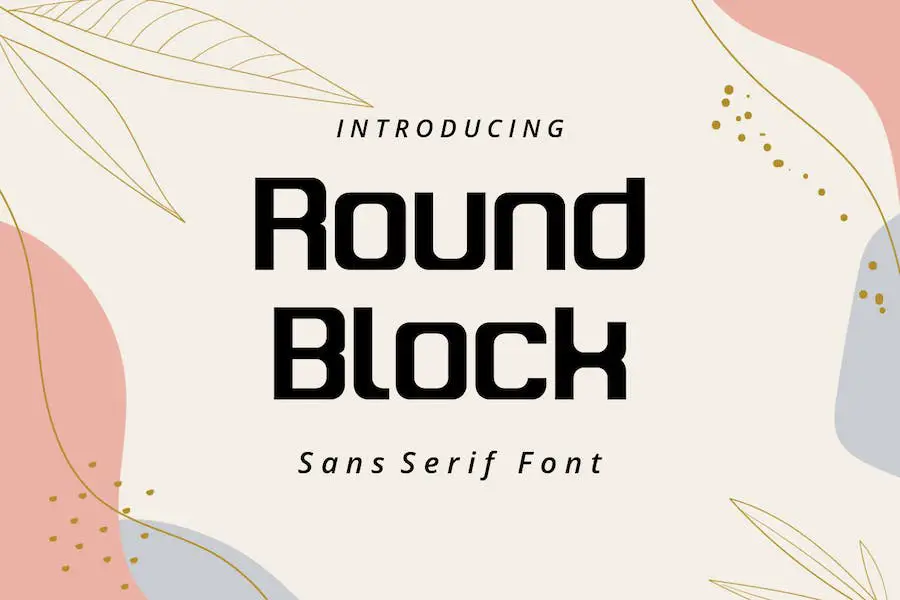
Round Block은 프로젝트를 향상시키려는 그래픽 디자이너에게 완벽한 현대적이고 부드러운 둥근 글꼴입니다. 테크노 산세리프 스타일로 스포츠 로고, 포스터, 헤드라인 및 인쇄 디자인에 현대적이고 세련된 터치를 더합니다.
이 다재다능한 글꼴은 표준 다국어 문자도 지원하므로 다양한 디자인 요구 사항에 액세스할 수 있습니다. 다가오는 이벤트를 위한 포스터 작업을 하거나 스포츠 팀의 로고를 만들 때 Round Block이 도와드립니다.
민트 라운드
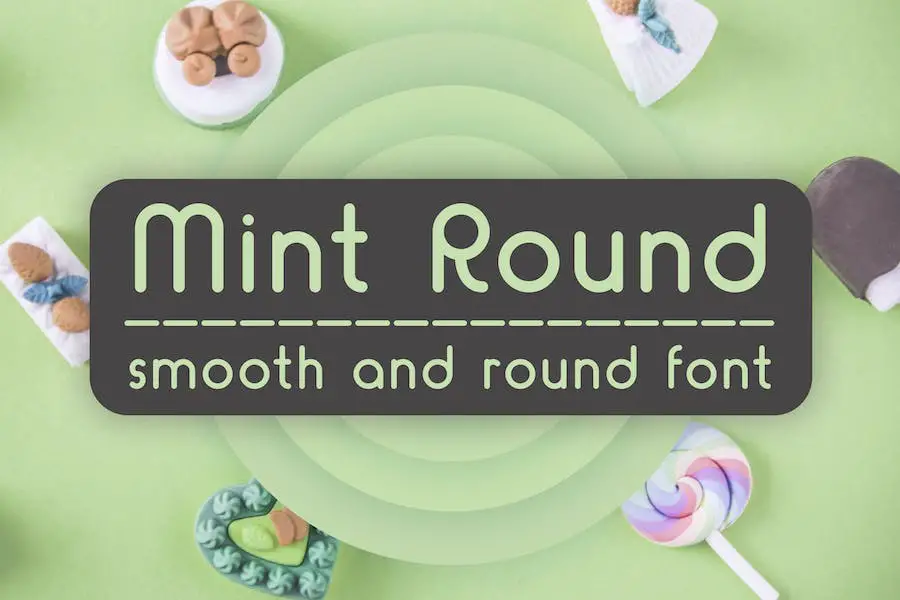
Mint Round는 디자인에 경쾌하고 현대적인 감각을 더해주는 부드러운 둥근 글꼴입니다. 단색, 윤곽선 및 인라인 변형이 있는 이 글꼴은 다양성과 창의성을 제공합니다.
Mint Round의 둥근 모서리와 매끄러움은 긍정적인 분위기를 자아내므로 프로젝트에 신선하고 독특한 모양을 추가하는 데 탁월한 선택입니다.
로고를 디자인하거나 눈길을 끄는 그래픽을 만들 때 Mint Round는 관심을 끌고 오래 지속되는 인상을 남길 것입니다. 우아함과 장난기를 더할 수 있는 기본 글꼴인 Mint Round를 사용하여 디자인에 부드럽고 현대적이며 둥근 느낌을 줍니다.
폰세카
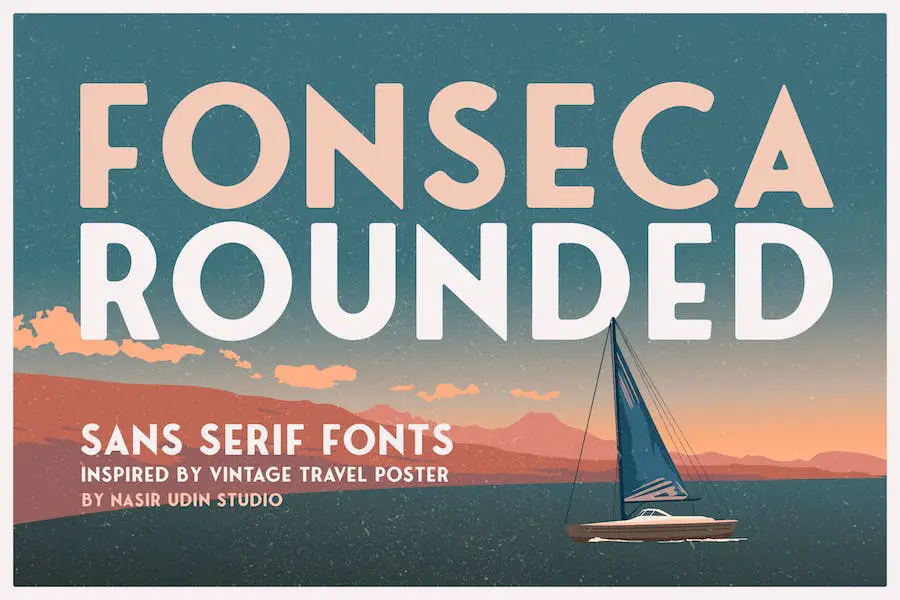
Fonseca는 빈티지 여행 포스터에서 영감을 얻은 It Rounded라는 산세리프 글꼴입니다. 현대적인 느낌과 시대를 초월한 매력이 있는 이 글꼴은 디자인 프로젝트에 우아함을 더하는 데 적합합니다.
제목, 로고, 브랜딩 프로젝트 등에 사용할 수 있는 It Rounded Bold Oblique 및 It Rounded를 포함하여 네 가지 글꼴로 제공됩니다. 글꼴 모음에는 It Rounded Bold 및 It Rounded Oblique도 포함되어 있어 창의적인 요구 사항에 맞는 다양한 옵션을 제공합니다.
328개의 글리프와 'LA', 'LE', 'LI', 'LO' 및 'LU'와 같은 문자에 대한 특수 합자를 특징으로 하는 이 글꼴을 사용하면 독특하고 창의적인 타이포그래피 구성이 가능합니다. 또한 문자 'O' 및 'E'에 대한 대체 문체를 포함하여 디자인에 훨씬 더 다양한 기능을 추가합니다.
아바포어 라운드
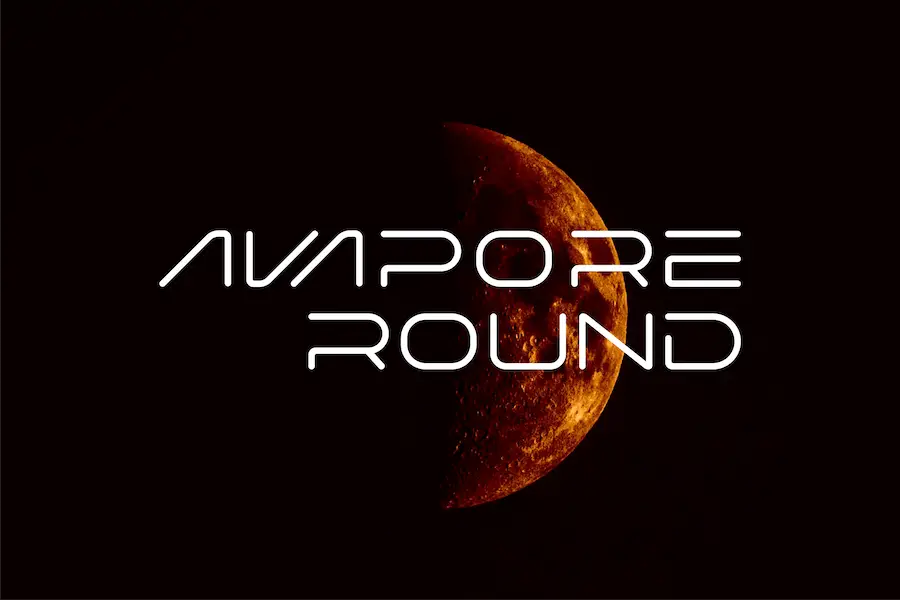
Avapore Round는 브랜딩 및 편집 솔루션 역할을 하는 넓고 둥글며 현대적인 산세리프 서체입니다. 이 글꼴은 다양성과 유연성을 제공하여 다양한 프로젝트와 매체에 적합합니다.
부드러운 둥근 글꼴, 현대적인 둥근 글꼴 또는 로고용 둥근 글꼴이 필요한 그래픽 디자이너에게 탁월한 선택입니다.
둥근 디자인과 매끄러운 곡선으로 Avapore Round는 모든 디자인에 친근함과 친근감을 더합니다. 넓은 구조와 현대적인 스타일이 돋보이며 모던하고 세련된 느낌을 연출합니다.
로고, 웹 사이트 또는 인쇄 자료를 작업할 때 이 글꼴을 사용하면 전체 디자인을 향상하고 시각적으로 더 매력적으로 만들 수 있습니다.
라운드 종류
Round Kind는 모든 디자인 프로젝트에 향수를 더해주는 환상적인 빈티지 디스플레이 서체입니다. 고급스럽고 현대적인 느낌의 이 글꼴은 로고, 초대장, 레이블, 잡지, 책, 연하장, 포장 등을 만드는 데 적합합니다.
지나친 탐욕
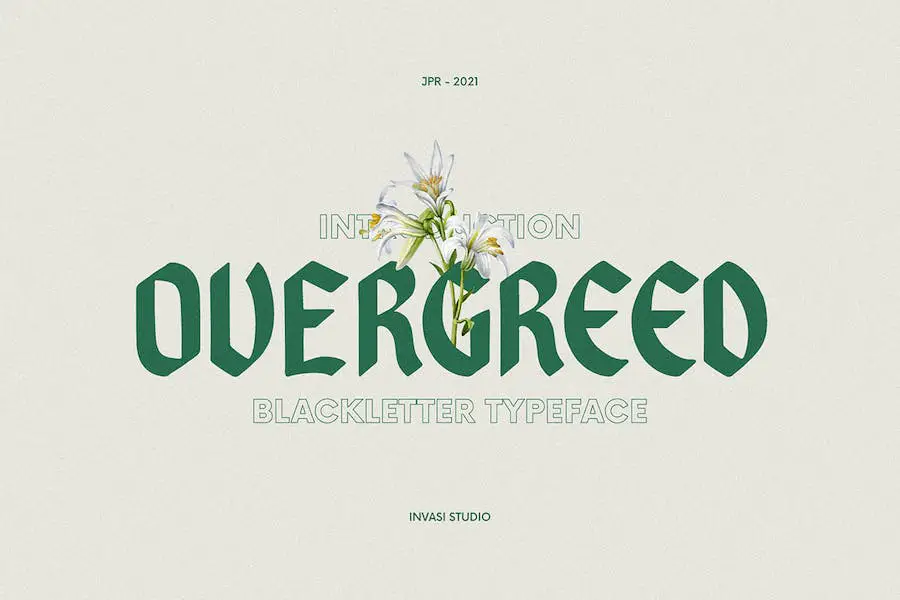
Overgreed는 현대적인 둥근 트위스트가 있는 멋진 블랙레터 글꼴입니다. 우아하고 대담한 스타일은 로고 작업을 하는 그래픽 디자이너, 둥근 글꼴을 찾는 타투 아티스트, 디자인을 향상시키려는 창의적인 개인 등 모든 프로젝트에 독특한 터치를 더합니다.
Overgreed는 세련되고 현대적인 미학을 제공할 뿐만 아니라 대체 문자와 다국어 지원도 함께 제공되어 다양한 디자인 요구에 적합하고 다재다능합니다.
매력적인 제목, 시선을 사로잡는 전단지, 기억에 남을 인사말 카드, 스타일리시한 제품 포장, 마음을 사로잡는 책 표지, 영향력 있는 인쇄 인용문, 전문적인 로고, 트렌디한 의류 디자인 또는 매혹적인 앨범 표지를 만들 때 이 글꼴을 사용할 수 있습니다.
둥근 포피
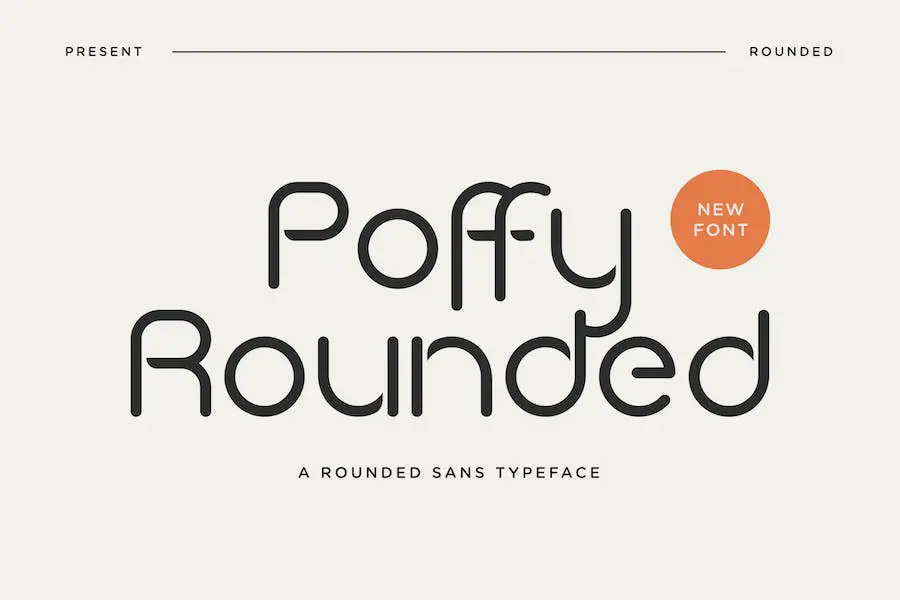
Poffy Rounded는 프로젝트의 디자인을 향상시킬 수 있는 둥근 Sans 글꼴입니다. 다재다능함으로 다양한 창의적인 아이디어에 매끄럽게 통합되어 차별화되는 독특한 터치를 더할 수 있습니다.
로고 디자이너든 그래픽 아티스트든 이 글꼴은 툴킷에 추가할 수 있는 완벽한 글꼴입니다.
Poffy Rounded의 둥근 디자인은 프로젝트에 따뜻함과 친근감을 선사합니다. 전체적인 미학을 향상시킬 수있는 장난스럽고 친근한 분위기를 더합니다.
어린이 브랜드 로고를 디자인하거나 소셜 미디어 캠페인을 위한 그래픽을 만들 때 이 글꼴을 사용하면 작품에 신선하고 현대적인 느낌을 줄 수 있습니다.
모라밋
Moramit는 프로젝트에 현대적인 스타일을 더하는 데 적합한 트렌디하고 대담하며 복고풍의 둥근 글꼴입니다. 우아하고 클래식한 모양의 이 글꼴은 브랜딩 프로젝트, 고유한 로고 생성, 시선을 사로잡는 웹사이트 헤더 디자인에 이상적입니다.
이 글꼴은 다양한 대체 글꼴과 합자를 제공하므로 창의력을 발휘하고 독창적인 디자인을 만들 수 있습니다. 로고 작업을 하는 그래픽 디자이너든 스타일리시한 글꼴을 찾는 회로 디자이너든 Moramit는 완벽한 선택입니다.
그 화려하고 유행을 선도하는 스타일은 프로젝트를 다음 단계로 끌어올릴 것입니다.
바렐모
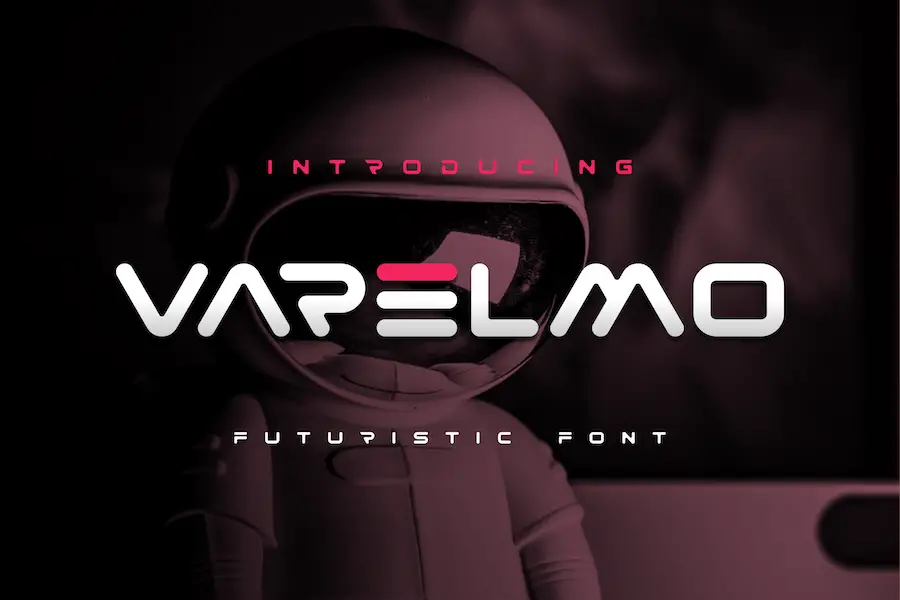
Varelmo는 It Round 글꼴로 알려진 현대적이고 대담하며 진정한 디스플레이 글꼴입니다. 이 글꼴은 브랜딩 프로젝트를 향상시키려는 그래픽 디자이너 및 로고 제작자에게 적합합니다.
또한 티셔츠 인쇄, e스포츠 디자인 등에 적합합니다. Varelmo는 다재다능함으로 모든 상황에서 프로젝트를 돋보이게 만들 수 있습니다.
Varelmo의 둥근 모양은 디자인에 우아함과 세련미를 더합니다. 대담하고 눈에 띄는 글자는 귀하의 메시지가 효과적이고 명확하게 전달되도록 합니다.
로고를 만들거나 그래픽 디자인 프로젝트에서 작업할 때 Varelmo는 세련되고 전문적인 모습을 얻을 수 있도록 도와줍니다.
암초
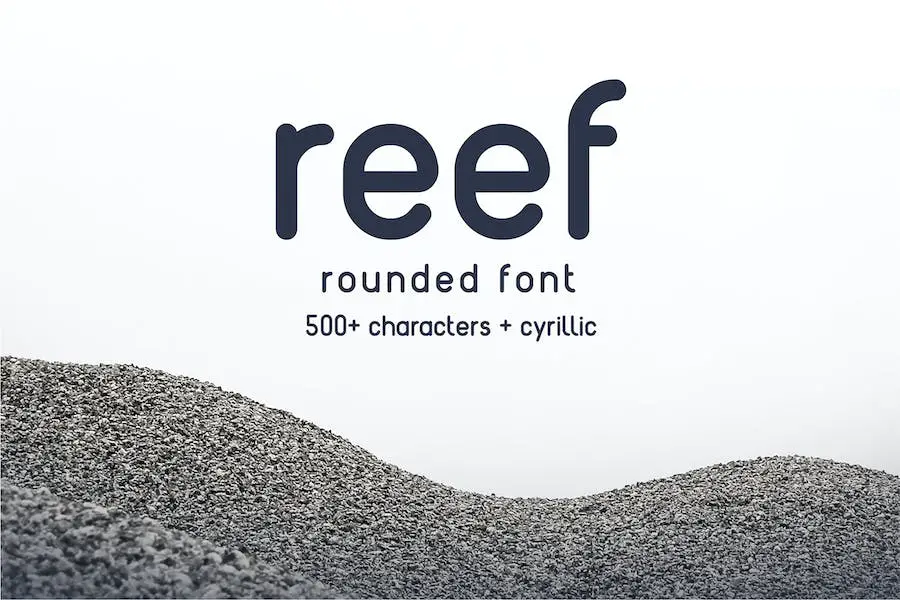
Reef는 프로젝트의 디자인을 향상시킬 수 있는 단순한 둥근 산세리프 글꼴입니다. 매끄럽고 구부러진 가장자리로 모든 그래픽 디자인이나 로고에 현대성과 장난기를 더합니다.
Reef의 깨끗하고 미니멀한 외관은 다목적이며 다양한 응용 분야에 적합합니다. 둥근 디자인은 프로페셔널한 느낌을 유지하면서 친근하고 친근한 느낌을 줍니다.
세련되고 읽기 쉬운 글꼴로 프로젝트를 향상시키려는 그래픽 디자이너라면 Reef를 고려해 볼 가치가 있습니다. Reef를 사용하면 시각적으로 매력적이고 기억에 남을 디자인을 만들어 청중에게 깊은 인상을 남길 수 있습니다.
간단한 둥근 가족
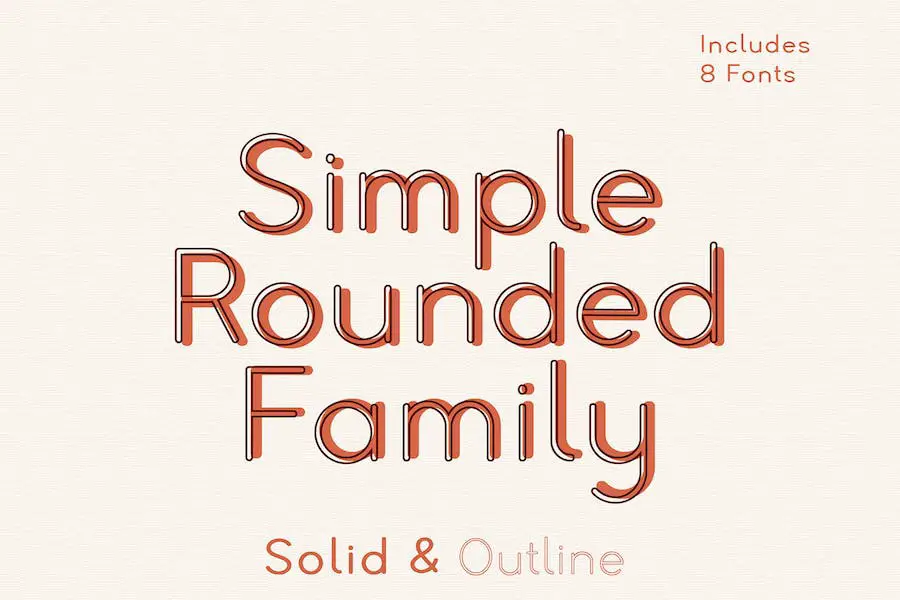
Simple Rounded Family는 로고 디자인 및 그래픽 디자이너에게 완벽한 글꼴 모음입니다. Simple Rounded-Thin, Simple Rounded-Bold 및 Simple Rounded-Outline과 같은 옵션을 통해 모든 프로젝트에 적합한 다양한 스타일을 제공합니다.
매끄럽고 현대적인 로고를 디자인하거나 눈길을 끄는 그래픽을 만들 때 이 둥근 글꼴은 우아함과 전문성을 더할 것입니다. 또한 Canva와 호환되므로 디자인에 매끄럽게 통합할 수 있습니다.
따라서 프로젝트를 향상시키고 돋보이게 만들고 싶다면 Simple Rounded Family를 사용해 보십시오. 감동이 확실합니다!
애드라인
Adline은 미니멀한 둥근 글꼴로 개인용과 업무용 모두에 적합합니다. 이 글꼴은 프로젝트에 현대적이고 세련된 터치를 추가하려는 그래픽 디자이너 및 로고 제작자에게 적합합니다.
깨끗하고 둥근 모서리가 있는 Adline은 모든 디자인에 신선하고 현대적인 느낌을 줍니다. 브랜딩 자료, 웹사이트 디자인 또는 모든 종류의 상업 프로젝트 작업을 하든 이 글꼴은 작업을 다음 단계로 끌어올리는 데 도움이 됩니다.
Adline의 단순성은 뛰어난 특성 중 하나입니다. 미니멀한 디자인은 독특하고 눈길을 끄는 외관을 유지하면서 쉽게 읽을 수 있도록 합니다. 둥근 모서리는 글꼴에 더 부드럽고 친근한 느낌을 주어 다양한 프로젝트에 적합합니다.
로고를 만들든, 포스터를 디자인하든, 소셜 미디어 그래픽을 제작하든 Adline은 깨끗하고 전문적인 모습을 얻을 수 있도록 도와줍니다.
식료품점
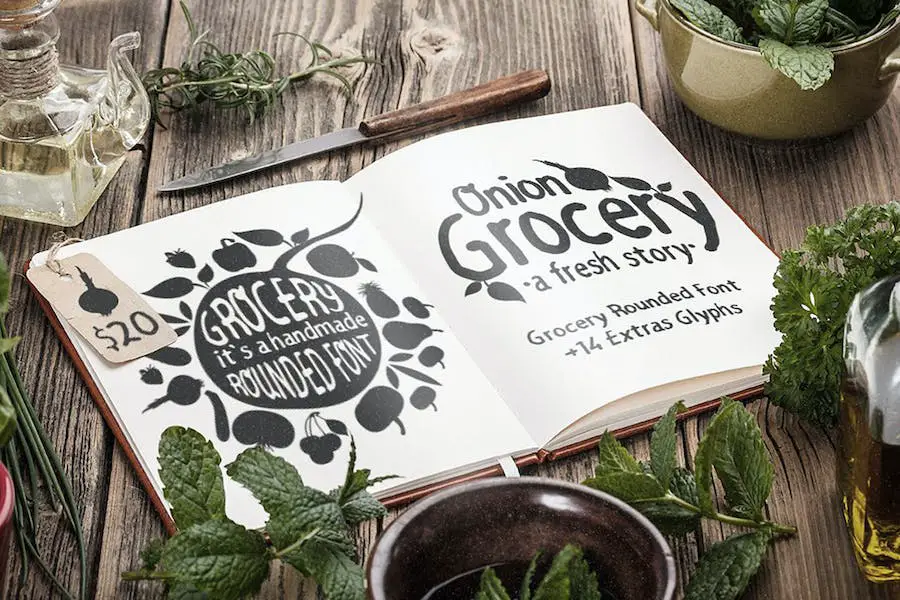
Grocery는 멋진 둥근 수제 글꼴로 프로젝트에 창의성과 매력을 더하는 데 적합합니다. 대문자와 소문자뿐만 아니라 모든 문장 부호와 14개의 사랑스러운 야채 및 과일 상형문자를 사용하여 다양성과 고유성을 제공합니다.
로고 디자이너든 그래픽 디자이너든 Grocery는 글꼴 컬렉션의 필수 아이템입니다. 둥근 디자인은 모든 프로젝트에 친근하고 접근하기 쉬운 분위기를 더해 눈길을 끄는 로고를 만들고 전반적인 디자인 미학을 향상시키는 데 이상적입니다.
또한 핸드메이드 느낌으로 개인적인 손길을 더해 작품을 돋보이게 합니다. 그래서 왜 기다려? 오늘 식료품을 구입하고 독특한 스타일로 디자인을 향상시키십시오.
아티스트
아티스트는 Roghan It Rounded Fonts라는 현대적인 글꼴입니다. 로고, 티셔츠 프린팅, e스포츠 등 다양한 브랜딩 프로젝트에 적합한 대담하고 실감나는 디스플레이 폰트입니다.
그것은 다양한 용도로 사용되며 모든 상황에서 두드러집니다. 둥근 디자인으로 디자인에 장난기와 창의성을 더해 시각적으로 매력적으로 만듭니다.
이 글꼴은 프로젝트 디자인을 향상시키기 위해 둥근 글꼴을 찾는 그래픽 디자이너에게 이상적입니다.
로고, 그래픽 디자인 프로젝트 또는 문신 디자인 작업을 하든 아티스트는 탁월한 선택이 될 수 있습니다. 현대적이고 대담한 미학은 디자인을 돋보이게 하고 청중에게 지속적인 인상을 남깁니다.
아우리
Auri는 모든 유형의 디자인에 이상적인 선택인 'It Round'라는 환상적인 산세리프 원형 글꼴입니다. 로고 작업을 하는 그래픽 디자이너이든 단순히 전체 디자인을 향상시키려는 사람이든 이 글꼴은 고려해 볼 가치가 있습니다.
둥근 모서리는 프로젝트에 우아함을 더할 수 있는 현대적이고 매끄러운 모양을 제공합니다.
Auri의 특징은 깨끗하고 부드러운 선으로 전체적인 매력을 더합니다. 모서리를 둥글게 처리하여 부드럽고 친근한 느낌을 주어 다양한 디자인 목적에 적합합니다. 다재다능한 이 글꼴은 인쇄물에서 웹 디자인에 이르기까지 무엇이든 사용할 수 있습니다.
Auri의 주요 장점 중 하나는 눈길을 끄는 로고를 만드는 기능입니다. 둥근 글꼴 스타일은 모든 브랜딩에 독특하고 기억에 남는 미학을 더합니다. 현대적이고 현대적인 외관으로 기업이 눈에 띄고 청중에게 지속적인 인상을 남길 수 있습니다.
플로키
Flocky는 Drizy 스튜디오에서 만든 현대적인 둥근 글꼴입니다. 현대적인 터치로 프로젝트를 향상시키려는 그래픽 디자이너 및 로고 제작자에게 적합합니다. 글꼴은 필요한 모든 필수 스타일과 함께 제공되므로 현대적인 테마에 이상적입니다.
대문자와 소문자, 숫자, 구두점 및 다국어 지원의 변형을 통해 Flocky는 디자인에 다양성을 제공합니다. 또한 대체 문자와 합자가 포함되어 있어 독특하고 눈길을 끄는 타이포그래피를 만들 수 있습니다.
이 글꼴은 작업에 현대적이고 둥근 미학을 추가하려는 모든 디자이너에게 필수품입니다.
클롭
클롭(Klop)은 부풀어 오르고 뚱뚱해 보이는 느낌을 구현하고 둥근 모서리와 자연스러운 형태를 강조한 디스플레이 서체입니다. 이 조합은 Klop에 기발하고 사랑스러운 모양을 제공하여 현대적이고 유쾌한 느낌을 추구하는 브랜딩 프로젝트 또는 패키징에 적합합니다.
대체 글리프를 활용하는 옵션을 통해 디자인에 고유한 모양을 쉽게 만들 수 있습니다. 현대적인 터치가 필요한 로고 및 프로젝트를 위한 둥근 글꼴을 찾는 그래픽 디자이너는 Klop이 훌륭한 선택임을 알게 될 것입니다.
다재다능하고 매력적이며 모든 디자인에 재미를 더합니다.
선회
Vertigo는 단순함과 전문성을 발산하는 현대적인 둥근 글꼴입니다. 미니멀한 스타일의 이 글꼴은 재미 있고 형식적인 디자인 모두에 적합합니다.
잡지 제목, 신문 헤드라인, 사무용 글꼴, 포스터, 책 표지, 로고 또는 배너용 글꼴이 필요한 경우 Vertigo는 다목적이며 다양한 유형의 프로젝트에 사용할 수 있습니다.
깨끗하고 날렵한 외관은 어떤 디자인에도 우아함을 더해 주므로 대형 아트웍에도 적합합니다. 따라서 프로젝트를 향상시키는 둥근 글꼴을 찾는 그래픽 디자이너라면 Vertigo를 고려해 볼 가치가 있습니다.
친차
Cincha는 그래픽 디자이너와 로고 제작자에게 완벽한 독특한 둥근 글꼴입니다. 귀엽고 재미있는 스타일에서 영감을 받은 이 글꼴은 책 표지, 포스터, 티셔츠, 인용구, 로고, 공예 등 다양한 프로젝트에 이상적입니다.
현대적인 둥근 디자인의 Cincha는 모든 디자인 프로젝트에 유쾌하고 눈길을 끄는 터치를 제공합니다. 다음 로고에 기발한 느낌을 더하고 싶거나 재미있고 생생한 포스터를 만들고 싶다면 Cincha는 완벽한 글꼴 선택입니다.
그래픽 디자이너를 위한 궁극의 둥근 글꼴인 Cincha를 사용하여 디자인에 신선하고 현대적인 느낌을 더하세요.
최고의 무료 둥근 글꼴
프로젝트 디자인을 개선하고 싶습니까? 최고의 둥근 글꼴 30개 컬렉션을 살펴보세요! 이러한 글꼴은 시각적으로 매력적일 뿐만 아니라 무료로 사용할 수 있습니다. 그래서, 왜 기다려? 다음 디자인 프로젝트를 위한 완벽한 글꼴을 찾아보세요.
뷰익
Buick은 프로젝트 디자인을 향상시키는 다재다능한 글꼴입니다. 둥근 모양으로 어떤 디자인에도 우아함과 세련미를 더합니다. 프로젝트를 돋보이게 할 글꼴을 찾는 그래픽 디자이너에게 적합합니다.
부드러운 둥근 모서리가 모던하고 세련된 느낌을 주어 문신과 로고에 잘 어울립니다. 글자의 곡률은 디자인에 장난기와 창의성을 더합니다.
Buick은 매우 인기 있는 글꼴로 만드는 다양한 속성을 제공합니다. 깨끗하고 단순한 라인으로 쉽게 읽고 이해할 수 있으므로 메시지가 청중에게 쉽게 전달됩니다.
캐피탈리아
Capitalia는 둥근 타이포그래피로 프로젝트를 향상시키려는 그래픽 디자이너에게 완벽한 다목적 글꼴입니다. 깨끗하고 현대적인 디자인으로 문신 디자인, 로고 및 부드럽고 둥근 미학이 필요한 기타 창의적인 프로젝트에 사용할 수 있습니다.
Tobias Sommer가 개발한 이 글꼴은 품질과 접근성을 보장하는 Google Rounded Fonts 컬렉션의 일부입니다.
Capitalia의 둥근 모서리는 친근하고 친근한 느낌을 주어 로고 및 브랜딩에 많이 사용됩니다. 현대적인 디자인은 세련되고 전문적인 모습을 연출하는 동시에 장난기를 유지하는 데 적합합니다.
문신을 디자인하든 로고를 디자인하든 Capitalia의 둥근 글꼴은 프로젝트에 독특한 터치를 더할 것입니다.
가지각색의 힘
Motley Forces는 Niskala Huruf가 디자인한 다재다능한 글꼴 컬렉션으로 상업적 용도로 사용할 수 있는 다양한 둥근 글꼴을 제공합니다. 이 글꼴은 현대적이고 부드러운 터치로 프로젝트 디자인을 향상시키려는 그래픽 디자이너에게 적합합니다.
Motley Forces를 사용하면 로고에 이상적인 다양한 둥근 글꼴을 찾을 수 있습니다. 이러한 글꼴은 브랜딩에 독특하고 전문적인 느낌을 더하여 비즈니스를 경쟁에서 돋보이게 합니다.
대기업을 위한 로고를 디자인하든 소규모 신생 기업을 위한 로고를 디자인하든 이 글꼴은 브랜드에 우아함과 창의성의 완벽한 균형을 제공합니다.
Motley Forces를 차별화하는 것은 부드러운 둥근 글꼴 모음입니다. 이 글꼴은 모든 디자인에 친근하고 친근한 느낌을 줍니다. 웹 사이트, 포스터 또는 소셜 미디어 게시물을 디자인하든 관계없이 따뜻하고 매력적인 분위기를 조성하는 데 적합합니다.
오딘 반올림
Odin Rounded는 둥근 글꼴 제품군에 속하는 다목적 서체입니다. 현대성과 부드러움의 터치로 프로젝트를 향상시키려는 그래픽 디자이너에게 적합합니다. Anonymous Foundry에서 만든 이 글꼴은 나머지 글꼴과 차별화되는 다양한 속성을 제공합니다.
모서리가 둥글게 처리된 Odin Rounded는 어떤 디자인에도 친숙함과 친근감을 선사합니다. 로고, 웹 사이트 또는 기타 시각적 표현을 만들 때 이 글꼴은 청중에게 지속적인 인상을 남길 수 있는 부드러운 터치를 추가합니다.
Odin Rounded의 주목할만한 기능 중 하나는 현대적인 미학입니다. 깔끔한 라인과 부드러운 곡선이 세련되고 시선을 사로잡는 컨템포러리 룩을 선사합니다. 이 글꼴은 최신 디자인 트렌드를 따라가도록 디자인되어 모든 디자이너에게 소중한 자산이 됩니다.
반다르
Bandar는 AfkariStudio에서 디자인한 환상적인 둥근 글꼴로 프로젝트 디자인을 향상시키려는 그래픽 디자이너에게 적합합니다. 모든 디자인의 전반적인 미학을 크게 향상시킬 수 있는 매끄럽고 현대적인 스타일을 제공합니다.
부드러운 둥근 모서리가 있는 Bandar는 로고를 만드는 데 이상적인 선택입니다. 부드러운 곡선은 우아함과 전문성을 제공하여 강력한 시각적 효과를 원하는 비즈니스 및 브랜드에 적합한 옵션입니다.
Bandar는 로고 디자인에 탁월할 뿐만 아니라 다양한 다른 디자인 프로젝트에도 적합합니다. 다재다능함을 통해 웹 사이트, 포스터, 브로셔 등과 같은 광범위한 디자인 응용 프로그램에서 사용할 수 있습니다.
둥근 에디
Eddie Rounded는 프로젝트에 세련되고 현대적인 디자인을 제공하려는 그래픽 디자이너에게 완벽한 환상적인 글꼴입니다. 이 글꼴의 부드럽고 둥근 가장자리는 모든 텍스트에 부드러움과 세련미를 더합니다.
Eddie Rounded를 사용하면 눈에 띄고 오래 지속되는 인상을 남길 멋진 로고를 만들 수 있습니다. 현대적이고 매끄러운 미학은 브랜딩 프로젝트를 위한 훌륭한 선택으로 디자인에 신선하고 현대적인 느낌을 줍니다.
Eddie Rounded의 가장 좋은 점 중 하나는 다양성입니다. 개인용 및 상업용 모두에 적합하므로 작업에 우아함을 더하려는 디자이너에게 탁월한 옵션입니다.
러빙 스노우
Kereatype의 Loving Snow는 프로젝트를 향상시키려는 그래픽 디자이너에게 완벽한 환상적인 둥근 글꼴입니다. 이 글꼴은 모든 디자인에 우아함과 세련미를 더해 로고, 브랜딩 및 기타 다양한 창의적인 노력에 이상적입니다.
부드럽고 현대적인 둥근 모양의 러빙 스노우는 디자인 프로젝트에 신선하고 현대적인 모습을 선사합니다.
이 글꼴에는 모든 디자이너에게 탁월한 선택이 될 수 있는 다양한 특성이 있습니다. 첫째, 모서리가 둥글게 처리되어 친근하고 친근한 느낌을 주어 다양한 프로젝트에 적합합니다.
기술 스타트업을 위한 로고를 디자인하거나 어린이 행사를 위한 브로슈어를 만들 때 Loving Snow는 작업에 따뜻함과 장난기를 가져다 줄 것입니다.
자유롭게 움직일 수 있는
Niskala Huruf의 Freely Movable은 프로젝트 디자인을 향상시키려는 그래픽 디자이너에게 완벽한 환상적인 글꼴입니다. 이 글꼴은 모든 디자인에 현대성과 부드러움을 더하는 둥근 스타일을 제공합니다.
독특하고 눈길을 끄는 속성을 갖춘 Freely Movable은 해당 카테고리의 다른 글꼴 중에서 두드러집니다. 둥근 모서리는 친근하고 친근한 느낌을 주어 로고 및 브랜딩에 적합합니다. 모든 프로젝트에 따뜻함과 전문성을 제공합니다.
Freely Movable의 주요 이점 중 하나는 다양성입니다. 웹사이트 헤더에서 소셜 미디어 게시물에 이르기까지 다양한 디자인 설정에서 사용할 수 있습니다. 세련되고 미니멀한 로고를 만들든, 재미있고 기발한 디자인을 만들든 이 글꼴을 사용하면 됩니다.
핀란드 반올림
Finland Rounded는 프로젝트 디자인을 향상시키려는 그래픽 디자이너에게 완벽한 환상적인 글꼴입니다. 둥근 모서리와 부드러운 곡선이 있는 이 글꼴은 모든 디자인에 부드러움과 현대성을 더합니다.
Craft Supply Co는 개인 용도로 이 글꼴을 무료로 제공합니다. 둥근 글꼴은 더 친근하고 접근하기 쉬운 느낌을 주는 경향이 있으므로 로고를 만드는 데 좋은 옵션입니다. 핀란드 라운디드의 깨끗하고 세련된 디자인은 다목적이며 다양한 디자인 스타일에 적합합니다.
Finland Rounded 글꼴은 명확하고 단순한 서체 덕분에 매우 읽기 쉽습니다. 둥근 모서리는 각 문자에 고유한 터치를 더하여 시각적으로 매력적이고 눈길을 끕니다.
M PLUS 반올림 1c
M PLUS Rounded 1c는 M+ 글꼴 프로젝트의 일환으로 Coji Morishita가 디자인한 환상적인 글꼴입니다. 깨끗하고 부드러운 둥근 모서리가 있어 현대적이고 스타일리시한 터치로 프로젝트를 향상시키려는 그래픽 디자이너에게 적합합니다.
M PLUS Rounded 1c의 뛰어난 특성 중 하나는 다용도성입니다. 로고를 만들든, 웹사이트를 디자인하든, 다른 창의적인 프로젝트를 작업하든 이 글꼴은 필요에 따라 쉽게 적응할 수 있습니다.
둥글고 매끄러운 외관은 디자인에 친근함과 친근감을 더해 시각적으로 매력적입니다.
자주 묻는 질문
원형 또는 기하학적 글꼴이라고도 하는 둥근 글꼴은 가장자리가 부드럽고 곡선인 서체입니다. 이 글꼴은 친근하고 친근한 모양이 특징이며, 더 부드럽고 장난기 있는 모양을 지향하는 디자인에 적합합니다.
둥근 글꼴은 다목적이며 다양한 디자인 응용 프로그램에서 사용할 수 있습니다. 로고 디자인, 브랜딩 자료, 헤드라인, 포스터, 소셜 미디어 그래픽, 웹사이트, 심지어 명함 및 브로셔와 같은 인쇄 자료에서도 잘 작동합니다.
그들의 장난기 있는 성격은 젊은 층을 대상으로 하는 프로젝트나 캐주얼하고 친근한 어조를 목표로 하는 프로젝트에 적합합니다.
둥근 글꼴은 디자인 프로젝트에 기발하고 친근한 느낌을 더할 수 있습니다. 그들은 종종 젊음, 창의성 및 현대적인 미학과 관련이 있습니다.
둥근 글꼴을 사용하면 더 매력적이고 따뜻한 분위기를 조성하여 콘텐츠를 청중에게 더 매력적이고 관련성 있게 만들 수 있습니다.
결론
결론적으로 프로젝트 디자인을 크게 향상시킬 수 있는 최고의 둥근 글꼴 30개를 살펴보았습니다. 클래식하고 우아한 것부터 현대적이고 유쾌한 것까지, 이 글꼴은 모든 창의적인 노력에 맞는 다양한 스타일을 제공합니다.